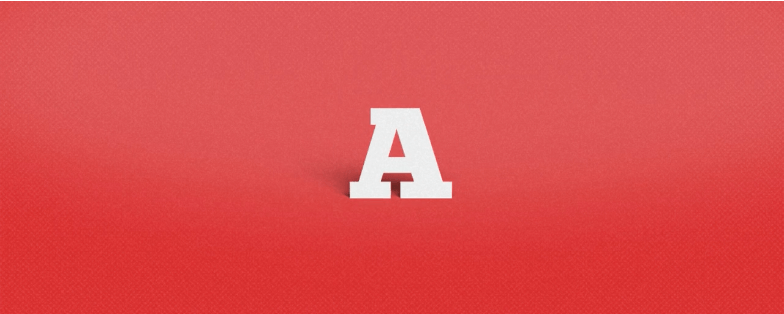
Typographie : Motion design et animation !
Cette semaine un numéro dédié à l'animation et au motion design en gardant comme sujet principale la typographie, toujours dans l'idée de compléter notre collection d'articles.
Nous avons sélectionné une série de 10 vidéos en motion design de qualité et récente, la plupart ont été publié ces derniers mois. De quoi nourrir votre inspiration avec de belles créations ! Les animations de typographies peuvent s'avérer très diversifiées, du simple affichage à la construction de lettre mettent en scène une grande multitude d'éléments graphiques. Un régale pour les yeux !